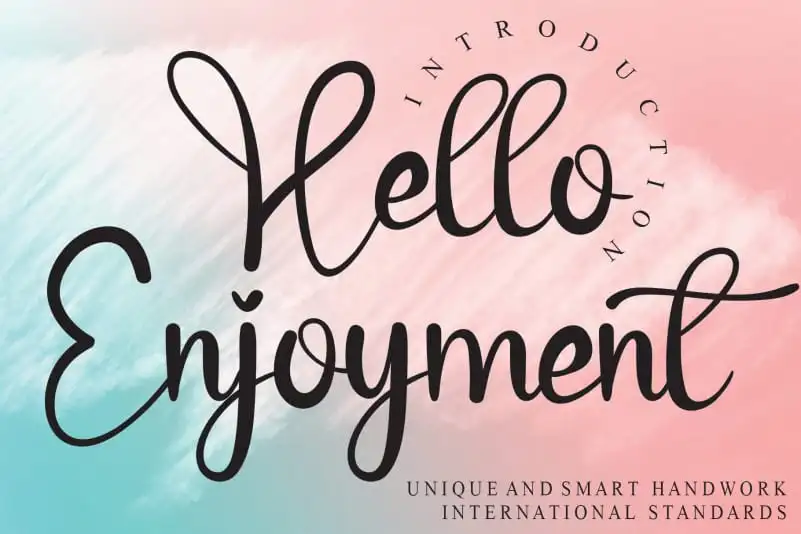
Aqui está uma descrição envolvente e natural para a página de download da fonte ‘Hello Enjoyment Calligraphy Font’, adaptada ao tom do cliente: O Hello Enjoyment Calligraphy Font é mais que apenas uma nova adição à sua biblioteca de recursos gráficos. Ele traz consigo um design único, criado com um toque especial por designers talentosos, o que promete transformar qualquer projeto em algo extraordinário e personalizado. Imagine a tranquilidade da escrita livreira se misturando ao encanto de uma caligrafia meticulosa, tudo isso dentro do conforto de sua tela. Este font foi pensado para dar um toque único à sua obra, seja ela uma publicação digital ou um projeto gráfico impresso. Através deste Hello Enjoyment Calligraphy Font, você terá a oportunidade de explorar uma nova forma de expressão visual. Não é apenas uma fonte mais; ele promete deslizar por suas páginas e moldar sua produção para que reflita seu próprio estilo único. Seja um designer gráfico, um blogueiro ou até mesmo um fotógrafo, o Hello Enjoyment Calligraphy Font irá transformar a forma como você apresenta suas ideias. Engane-se se pensar que ele é apenas uma fonte de escrita; é um complemento para seu arsenal criativo que certamente deixará sua marca.